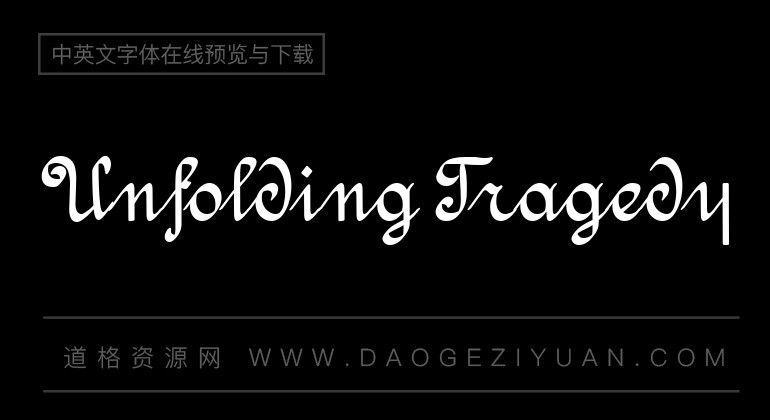
Unfolding Tragedy
Unfolding Tragedy 字体是一款灵感来自经典的文本类型的字体。它的特点是细节丰富,具有细腻的曲线,比较明朗,易于阅读。这款字体适用于各种文本类型,如书籍、文章、广告等,可以营造出一种悲伤而又唯美的氛围。它的字体风格较为传统,可以给人以经典、庄重的感觉,也可以让文本更加优雅。
Unfolding Tragedy是一款非常不错的手写艺术字体,具有很好的视觉感,适合于文化类的宣传设计、商业类品牌的广告和产品包装设计以及个性化文字排版等较多场景。